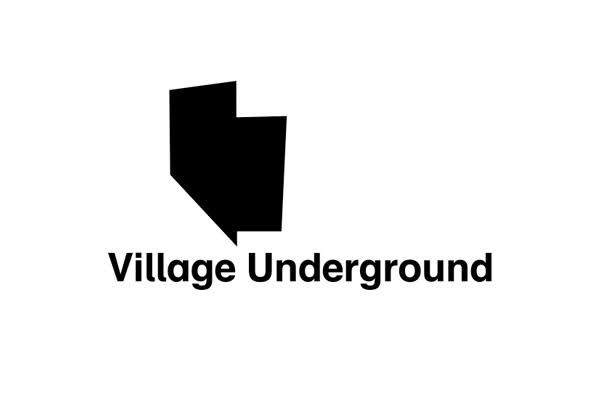
Puh! Bis aufs a und das l ist die der Helvetica wie aus dem Gesicht geschnitten. Ich würde tippen, da wurden fürs Logo die beiden Buchstaben angepasst.
(Denn die vergleichbaren Schriften, die mir einfallen, die zumindest so ein l haben – National und Akkurat – sind sonst zu anders. Und so ein a haben die auch nicht … Hm. Gibts noch mehr solche?)